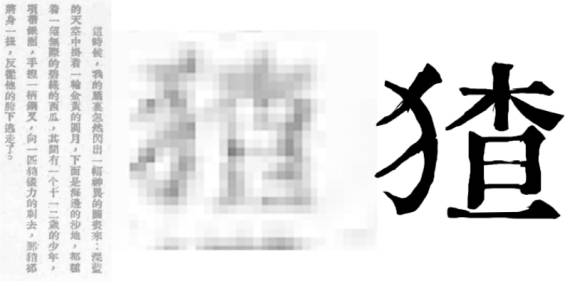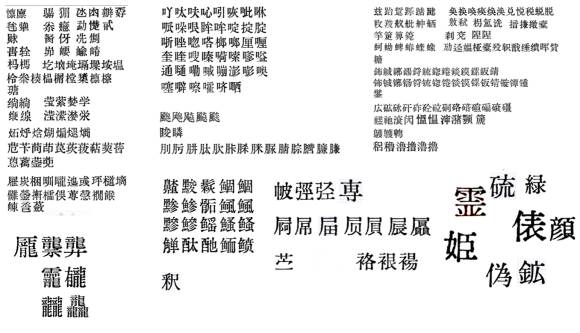
汇文明朝体
字体风格: 明朝体
一、简介
汇文明朝体制作始于2019年1月份。因一切开始于是我扫描《文汇报》上面的《汉字简化方案草案》。
后来又收集、扫描了各种历史文献资料,汇总挑选而形成了这样一款字体。故名「汇文明朝体」。
汇文明朝体的字形来源主体为五六十年代官方各种汉字改革文件。简体字部分基本复原汉字简化后、字形改造前的书籍印刷体样貌。繁体字、传承字部分基本还原民国至共和国初期字形样貌。是比较原滋原味的旧铅字印刷风格。
二、收录范围及规则
• 全覆盖大陆「GB2312」标准
• 全覆盖台湾「常用国字标准字体表」
• 全覆盖日本 常用、人名用、表外汉字表中的新字体
• 基本满足日常使用。
收录规则大致如下
● 旧字形有单独编码,但是简体汉字标准 和 繁体汉字标准日常都使用新字形的,都从旧(但采用不同来源让字形有所区别)
● 简体汉字标准 和 繁体漢字标准使用不同编码的,保留新字形,各从其形
● 中日共有简化字 编码相同者 从中(所以日文显示有时候很别扭)
● 中国特有简化字 从旧(按最早公布之字形)
● 日本特有新字形 从旧从异
● 个别罕见异体字 按照个人喜好 从异
● 不追求部件寫法統一
三、字形来源
(以下罗列书名按收录先后顺序排列,后收的书中如果有效果更好的字会替换掉前面的字)
● 简化汉字以及所对应的繁体字
来源于《简化汉字方案》《简体字总表》
● 传承字
来源于《通用汉字表草案》《新华字典》
● 异体字
来源于《简化汉字方案》《第一批异体字整理表》
● 日本新字形及日语常用字
来源于
《新字体汉和新辞典》1995
《日本常用汉字表》上海科学技术出版社
● 部分生僻字
提取自 汇文筑地五号明朝体(517字)
櫜弗艴攴釜吡呤呦哂咿唏喏啉啁啜喈喁喙嗍嘌嘧噍噌噔嚆囗囡圄圊圉幞忿忻忮怛怍恂悝悃悒悱惴愀慊慵恚慝懋烽煽焯焱煜煊熳燔燹爝汔汜沆泗泠泫洇洄洙洎洳浼渫湎湫湓溘漭溥溻溟澶濂瀹捂拊拶掎掊揠揄掾搠搦擐擗攉弘鬻屮屣戾扃猾狙狃狷猊夤庀庋庥庳廒廑廨疚疰痍痤瘐瘀瘕瘙瘼癀瘭瘵癃瘳癯仞仳仵佞佚佬傈佗伲佶侑侉佾俣俜倬倮僖儒僦儇砣磔礴黼芯芊芄芾芴芟苷苴苒荑荏莩堇菽萑萆菹菀菡葑葳葸蓁蓍蓐蓊甍蔟蕖蕞薤薹蘩礻祓祚靡峭崖岈岫崧崽嵬嵋豳徂戍弑彤旬尹釉予豫馘兕胤毓鼗亟鼐孛嘏厝剞剡劂劓亠羸冱謦卩卺阼陬陲陴隗郢郛鄣劬哿叟矍廾弈奕匏迓迕迨逖逶逭遄遑遒遨遘遛邂彐彖凵鬯厶坌圯坫坼坭垤埏垠垸埸宀搴寤褰妤姝娉婧嬗媼嬖孀孥畿巛甾玟珉珩琪琰琮琚璀璨杪杵杼柰枰柙柚栲栝桕桴棼椹楂槎楹榱槊槭樾檠橐歿軹戩檑檗殂殛殪甓旰昊昃炅曷昱晟晏晡暝暾曛曦牾擘耄毳毹氅氤牖爰肜胂胙胗胲脞腴腧媵膂欷欹歃觳旆旄旃旒眄眚眢睇瞽畎畋罘罟罹盥蠲銎矧稃稂穰皈皤翊穸穹窀窬裎裾襻穭耔耜耦耋耵聆虍虺蚨蚍蚋蚧蚪蛩蜚蜷蝌蜈螽笄笫笮笞筌筮箝篚篥篪簏簇臾舁臬舡舨舸舳艉艋艏艚艟艨粢糗艮翥翌綮繇豇酎酤酡酲酹醅醍醢醪醵趴蹋跫跗跬跣踔踟踣蹀踽蹯躅貅貘貔觫霈霪隼鞫骰魃魈饔髟髹鬈黧黥鼢鼷奐閎閌嚌幬瀦萇薟彥袞詵隉勱媼歿軹戩綞繢飇鐔穭鵯艤鮞鱝
●其他生僻字
来源于
《语文新字典》1977星洲世界书局
《国音常用字彙》1938
● 基础拉丁字母及阿拉伯数字
来源于
《通用汉字表草案》
《标准电码本》1964
● 俄文字母
来源于某本俄语字典前的字母表,实在找不到了……
● 希腊字母
来源于
《日本常用汉字表》上海科学技术出版社(没错,希腊字母来源于一本日语书…)
● 注音符号
来源于《潮汕新字典》广泰书局
● 其他拉丁字母、符号、平片假名及个别汉字
来源于Oradano明朝
● 拼字自绘(274字)
●「猹」復刻自
《新青年》第九卷第一号 鲁迅《故乡》
实在是太糊了…全靠想象
四、后面的废话
二零二一年一月十二日
元旦之后难得的休息天,想着连二零二零都结束了,有些事也该告一段落了,于是我打开了许久未动的电脑。
二零二零真的是特殊,疫情改变了一切原有安排和生活习惯,唯一的「好处」可能就是让我被迫有了大把的时间,来全身心的投入做一些本来来日方长的事。
赋闲在家的几个月,我这工作强度可不比上班低,从起床到睡觉,我都在扫描仪、PS、fontcreator之间来回切换。自己给自己007,换来了父母的各种吐槽,也让我能远离纷乱的互联网,毕竟那段时间一上网就会被各种负面消息和情绪包围,专心做事能让心里好受一些。这段时间进展真是突飞猛进。
到三月底开始线上办公了,进度也就慢了下来,但还是能抽空徐徐推进。差不多到六月初常用字补齐了,嵌入手机用了一下感觉不错,就还剩一些实在找不到现成的铅字扫描的字码没有解决,于是我开始拼凑造字了。
然而到了7月12日,一纸召唤令,奉旨还朝,我嗻了,也就鸽了。
和前半年的空闲完全相反,回朝之后的忙碌超乎想象,第一次的冲上火线带兵打仗,焦头烂额不得余裕,理所当然的身心疲惫,理所当然的鸽了爱好。一鸽就是小半年。
二零二一年一月十二日
元旦之后难得的休息天,想着连二零二零都结束了,有些事也该告一段落了,于是我打开了许久未动的电脑。其实本来就没剩多少了,一整天弄完绰绰有余,好久没在字海中游荡一回来觉得倍感亲切,不知不觉又是半夜。
一月十三日凌晨一点三十二分,封装完成,安装到电脑,打开Word测试,可以。这就告一段落了。
高兴吗?高兴。兴奋吗?还行。
可能是中间隔了太久断了气口,也可能是实在还有一些生字不能显示总觉得没有彻底结束,我没能感受到那种做完一件大事的兴奋感。
2019.1.24 – 2021.1.13,倒也不算长,毕竟还断了不少时间。
但终究还是达成立项当初的目标了。
在家007时我就在想,干嘛这么拼呢?父母也常在问做好了要拿出去卖吗,我也不是没想过,万一火了岂不是赚翻了?不过还是算了,我哪是那种会做生意的人。况且
本来这个东西:铅印风格、旧字形字体,就很小众,很少有人了解,小众到大家一起看民国电视剧电影,出现新字形字体的时候,只有我在那儿难受得脚趾抓地。
而且我做的这算啥,算字体设计吗?我觉得很难算,我最多就是按照自己的审美去挑选了一些好用的有意思的字形进行封装,甚至还有很多是没得选的,只能用那样的糟糕的字形,哪有什么设计…
但我就是喜欢这个这个味儿,就是要曲线感人,就是要异躰穿插,就是要同样的部件各有各的写法。哪儿会有人偏偏爱好这个啊?还爱得这么具体,这么深。
而我就是喜欢它,想把它介绍给大家,希望大家也能喜欢。就是这样的心情,让我终于还是弄完了它,发了出来。
废话到这儿也差不多了,也算是顺便记录一下二零二零我是怎么过来的。废话这么多还真是不好意思了。( ´_ゝ`)
上面也提到,本字体平片假名及一些符号来源于Oradano明朝,其实要说起来,本字体的史祖就是Oradano明朝。
因为最开始做的时候,我对于字体的字距、大小什麽的,完全不会调,也不知道要怎麽设置各种数据,所以就直接取了「Oradano明朝」这个字体作为壳子,把裡面的东西一一替换成我的字形,慢慢地替换到最后,才形成了汇文明朝体。就是説,其实这是一艘忒修斯之船。